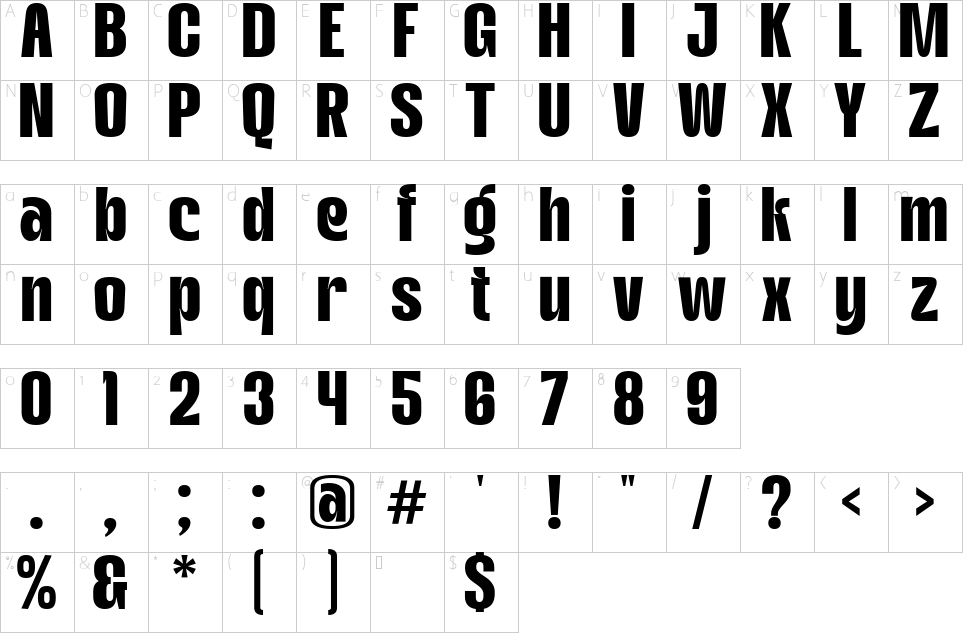
Gotkin Font é uma opção gratuita e versátil para quem busca uma fonte moderna e elegante para projetos digitais. Desenvolvida pela Megatype, a Gotkin foi projetada para agregar aos seus projetos, seja em design gráfico, blog, ou mesmo para criar efeitos visuais de forma criativa. Com seu design minimalista e sofisticado, a Gotkin é uma ótima escolha para quem busca um equilíbrio perfeito entre simplicidade e presença. Além disso, a fonte tem sido amplamente utilizada, já tendo sido baixada mais de 700 vezes, o que indica a sua qualidade e popularidade. Se você está procurando por uma fonte que não comprometa a qualidade gráfica em nome de algo mais, a Gotkin pode ser uma excelente opção. Baixe-a agora e dê um toque inovador ao seu próximo projeto!